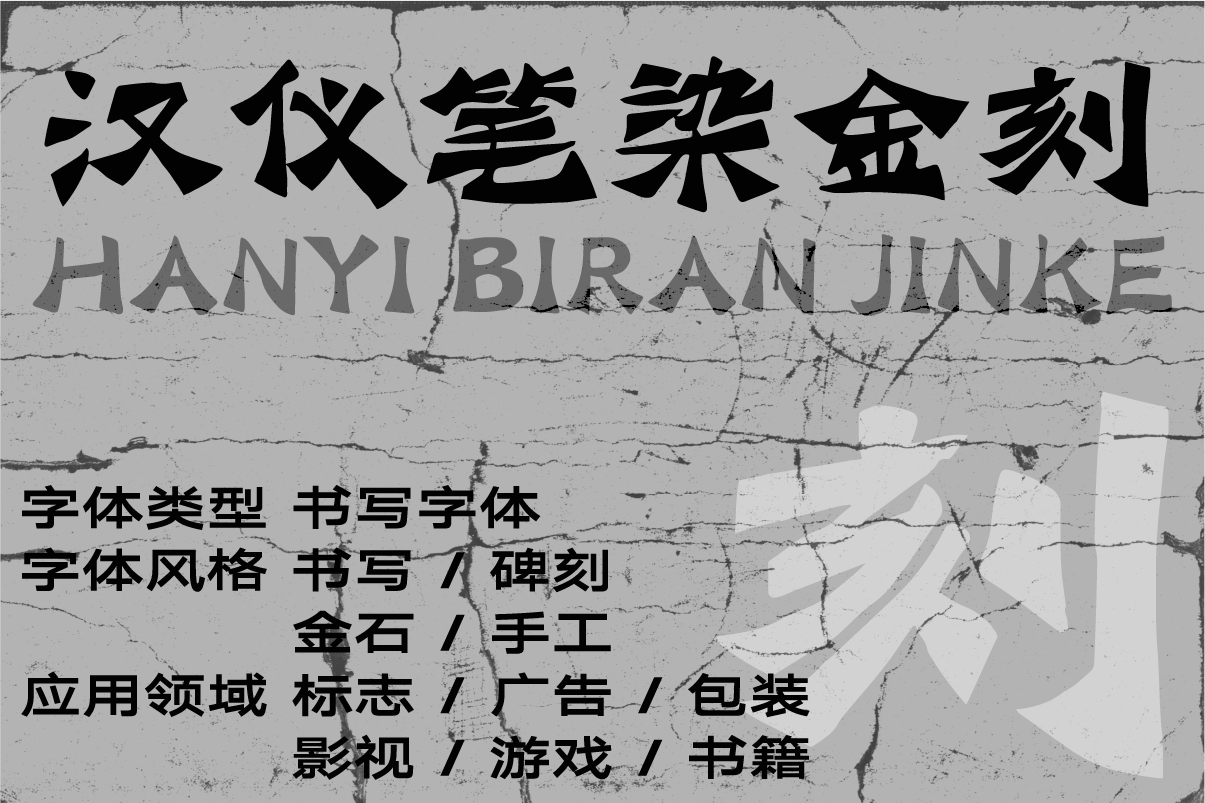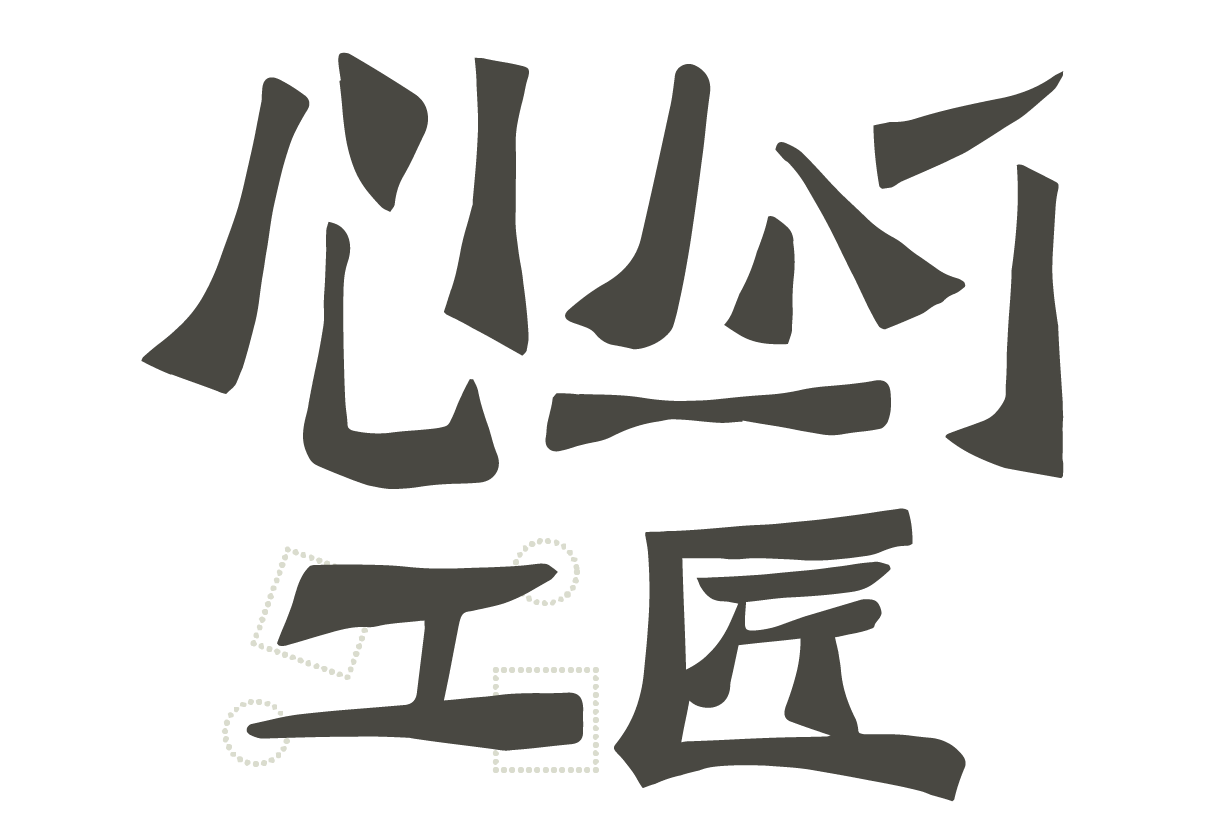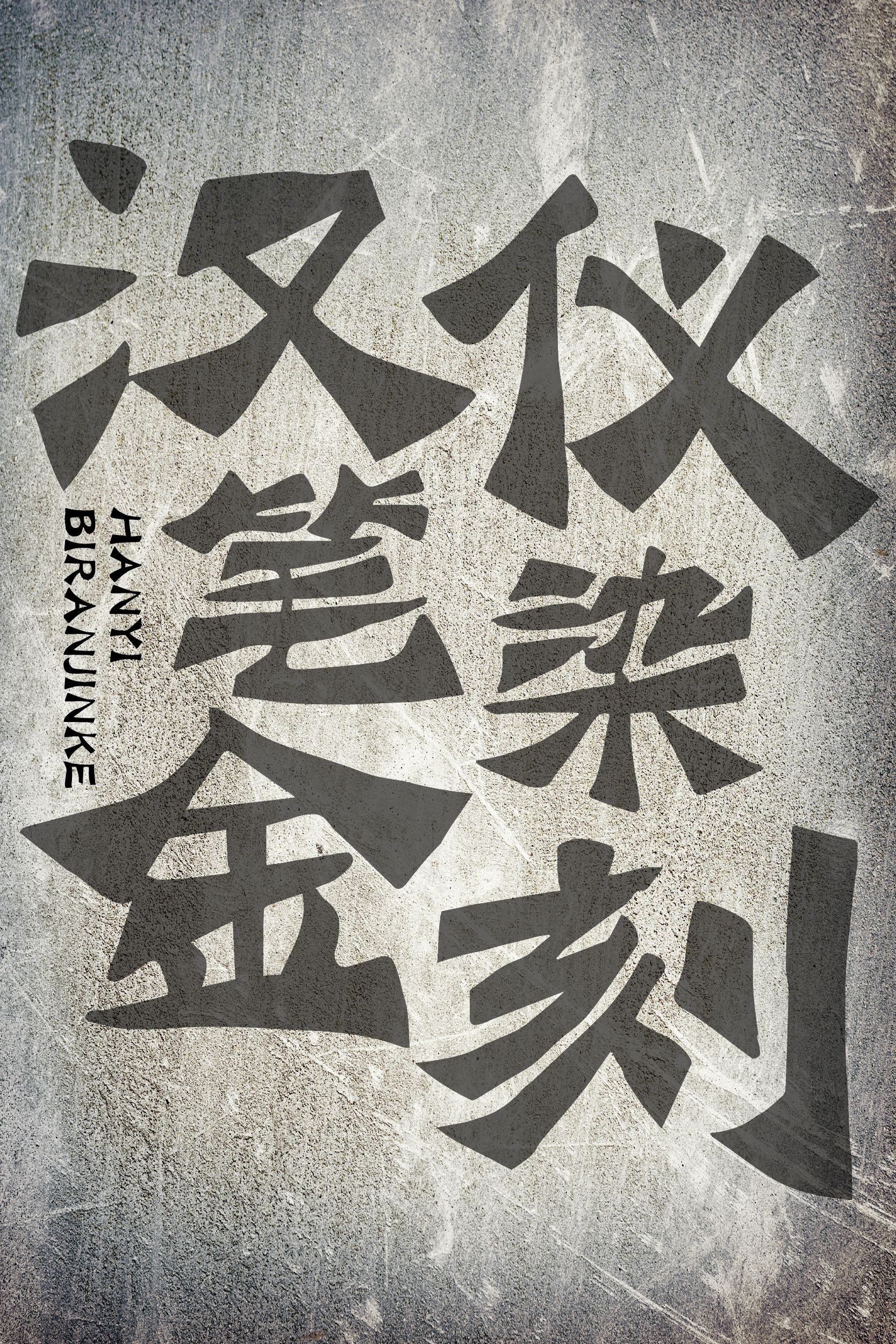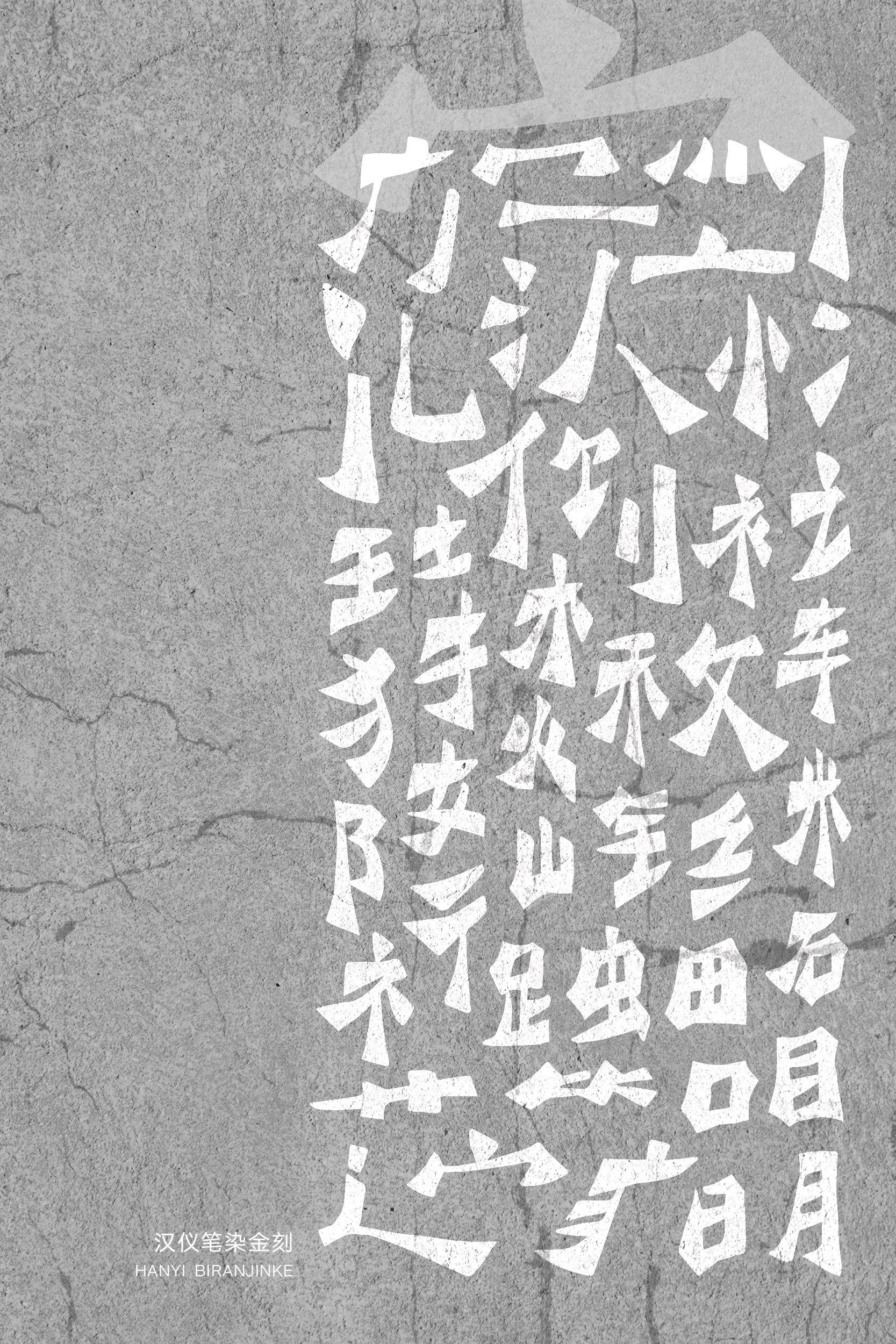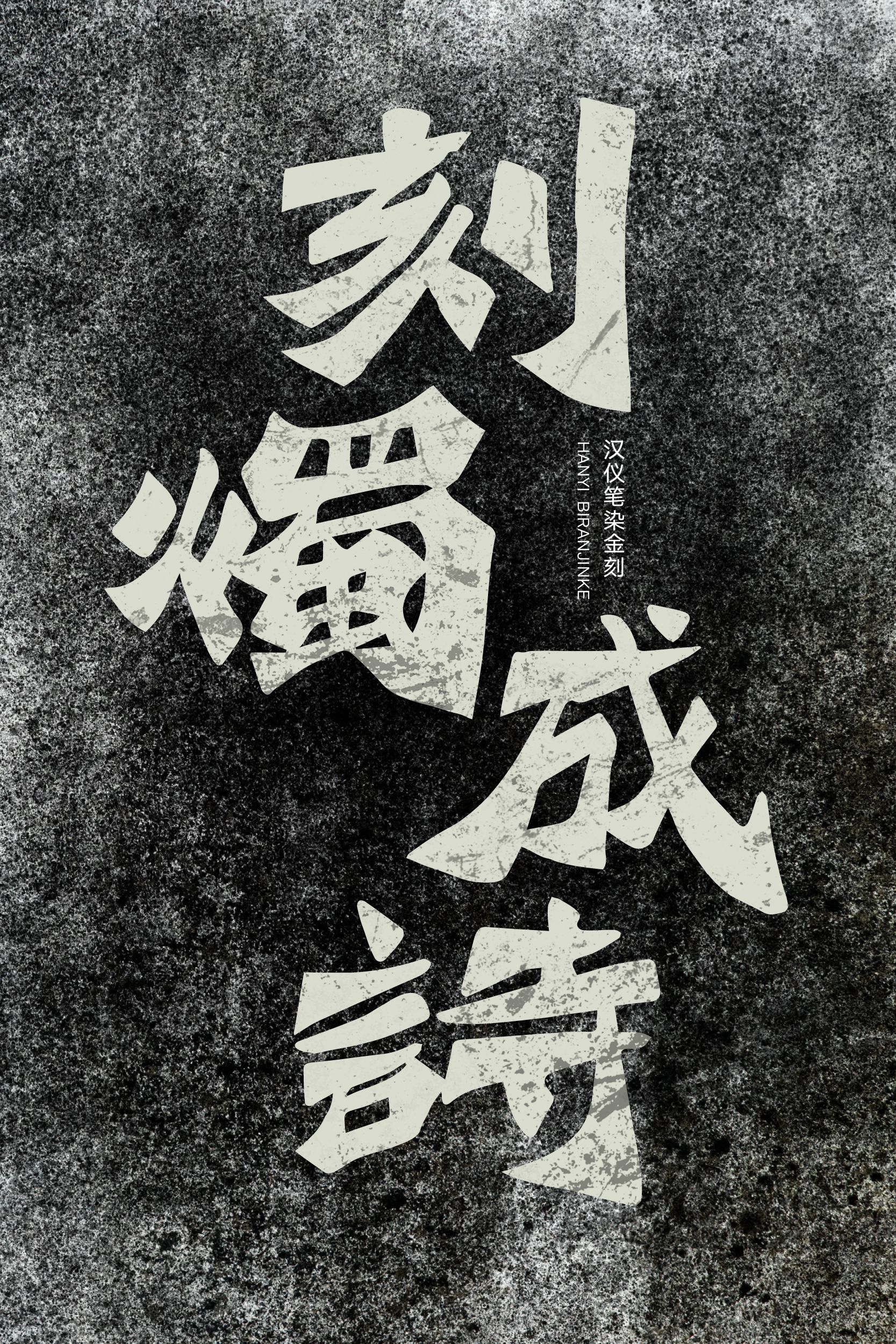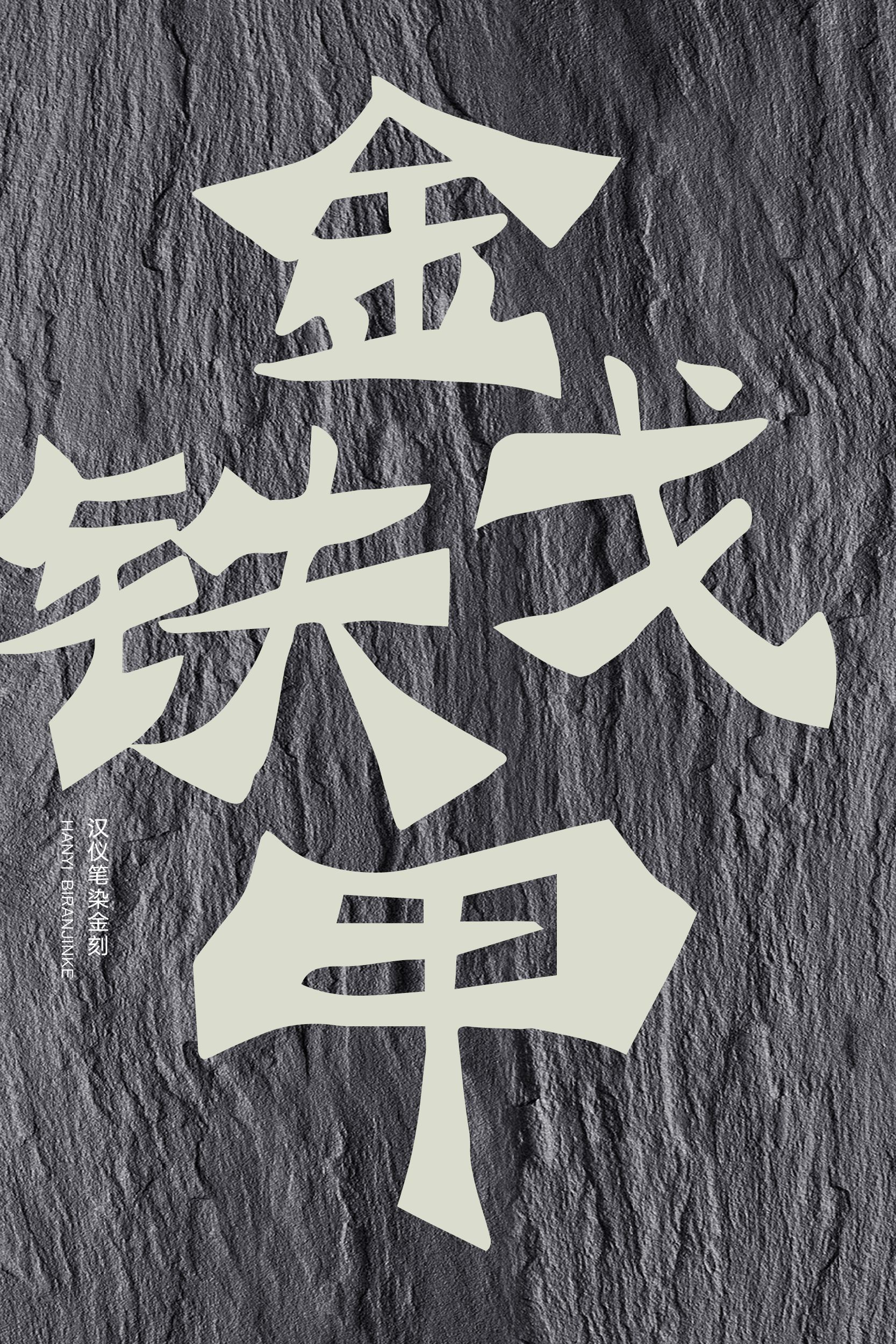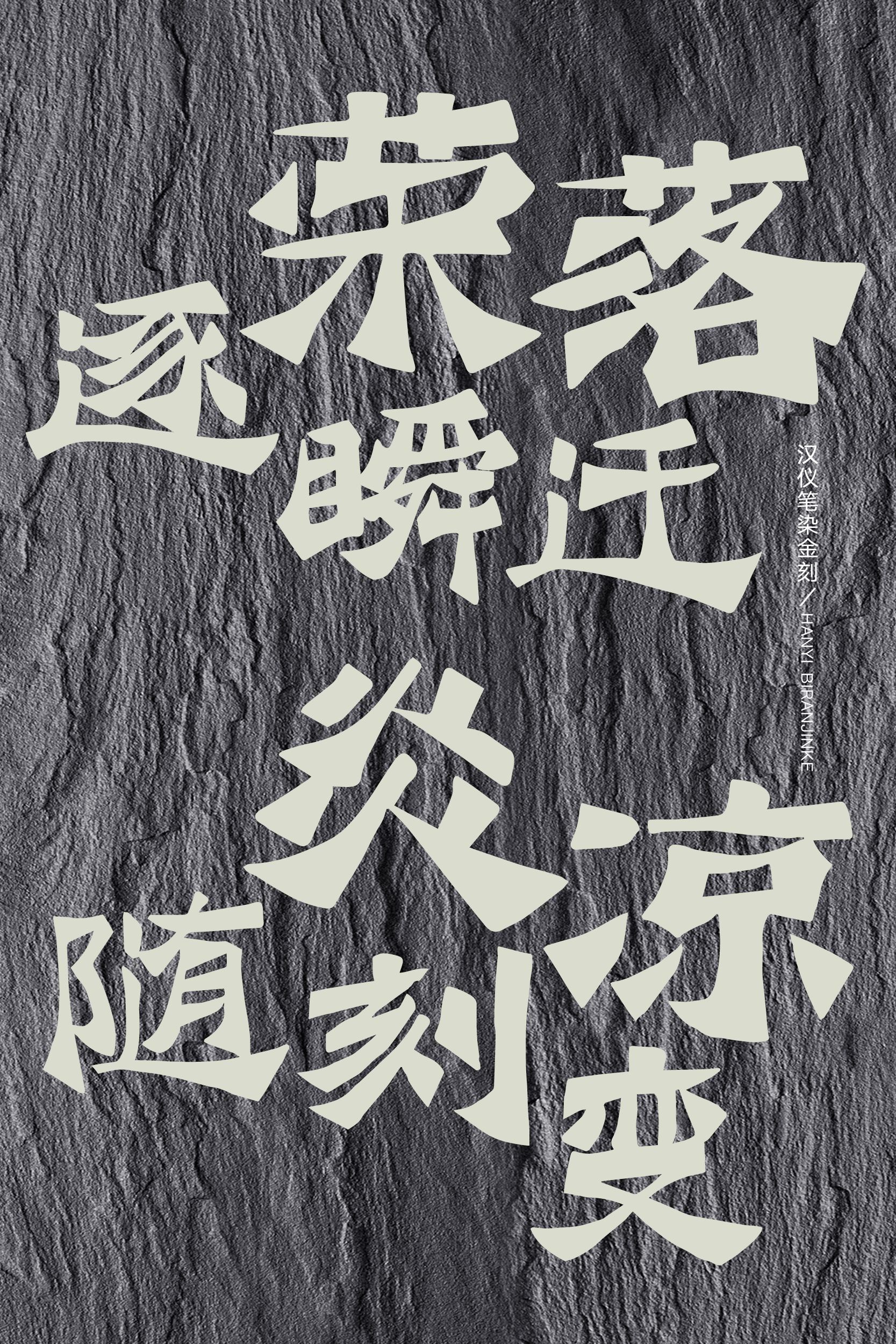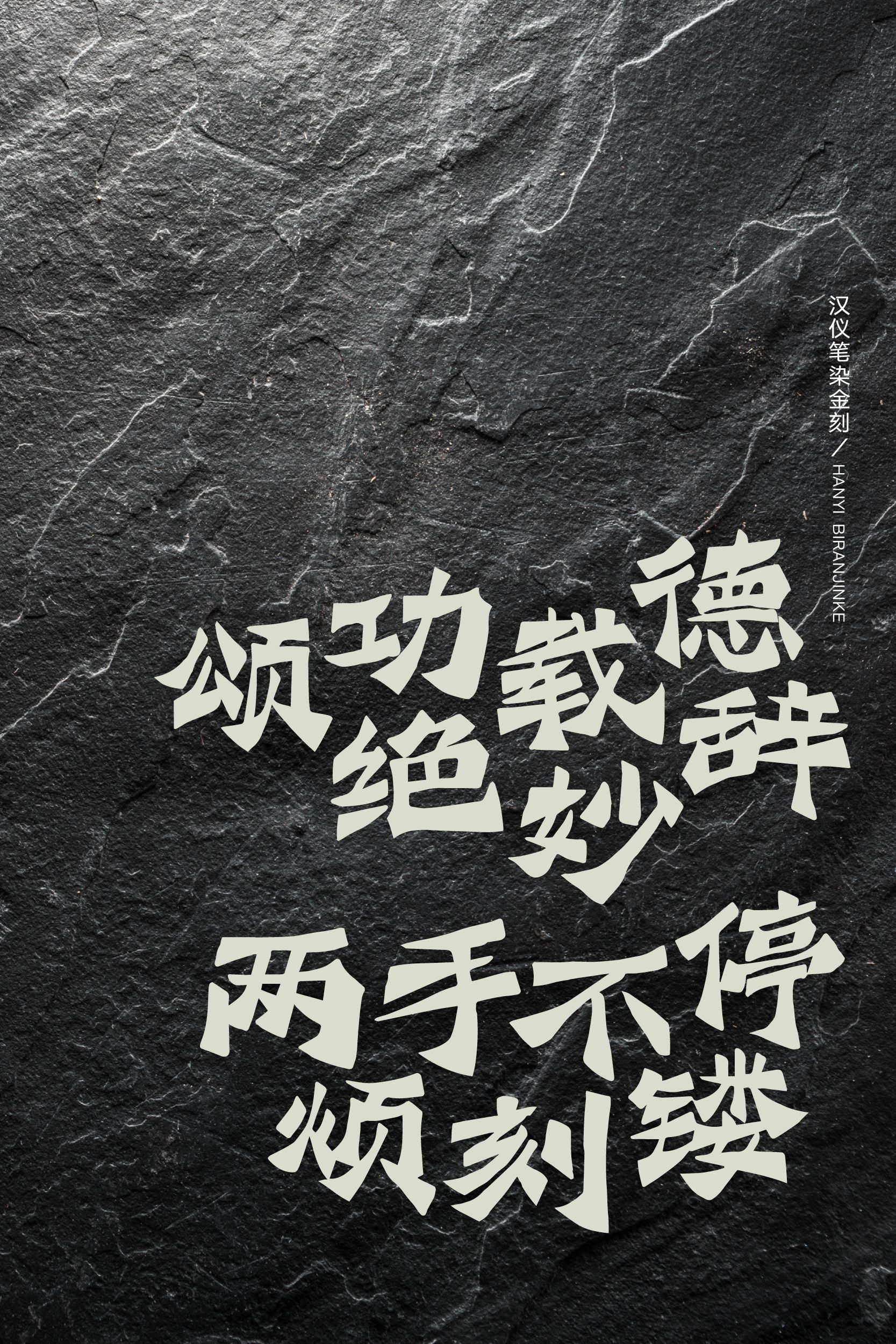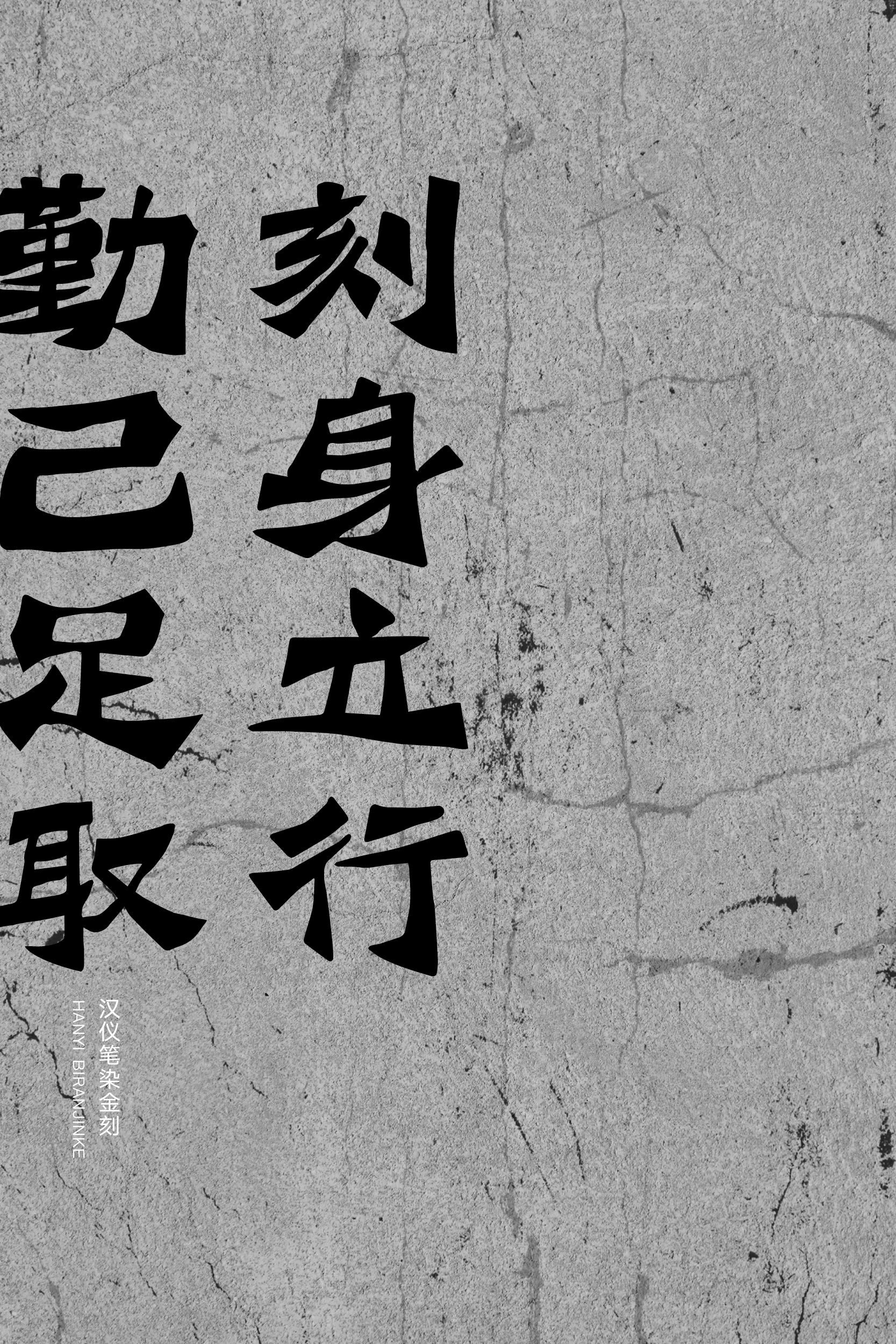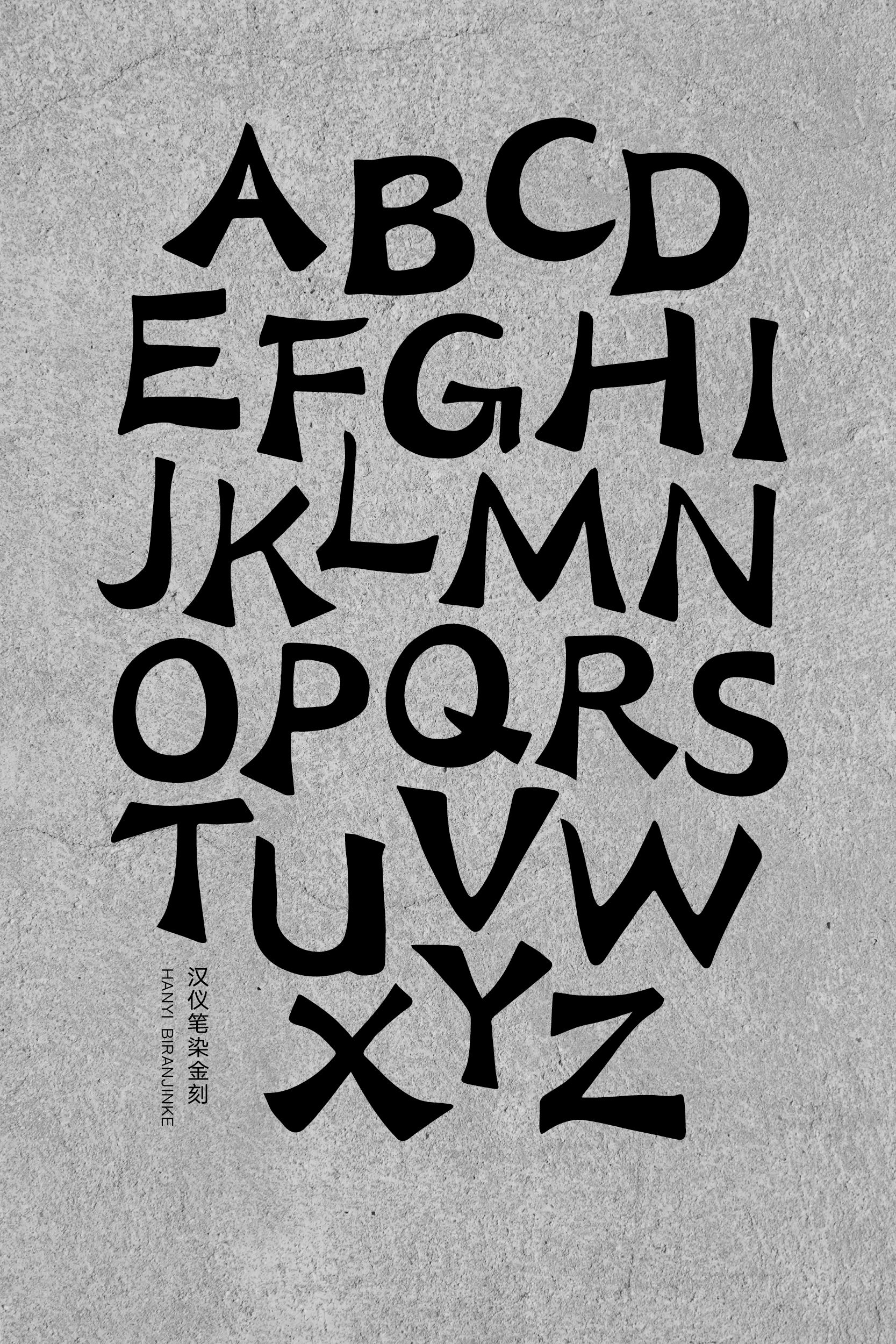
汉仪笔染金刻
汉仪笔染金刻,方笔尖角添金石味,刀刻边缘显手工感,是一款手刻风格的书写字体。字形扁宽而多变化,笔画粗细对比强烈。这款字体于奇险中见均衡,硬朗而生动,适合较大字号、较少字数的文本排版,可以传递出浓重的时代感与手工感。
字形扁宽,重心均衡。
笔画粗细对比强烈。
笔画转合与断连颇具手工刀刻感。
西文部分保留方笔尖角,融合书写与刀刻的韵味,中西文匹配和谐一致。